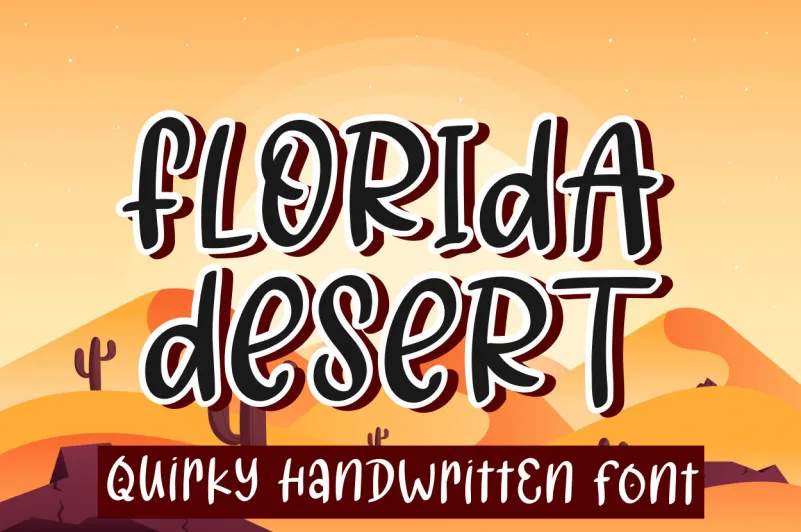
Esta é uma fonte display amigável e quirk, perfeita para quem quer dar um toque especial às suas criações visuais. O “Florida Desert Font” da designer sugiharto1790 será a escolha ideal para adicionar leveza à sua identidade visual, seja em cartões de boas-vindas elaborados ou posts sociais cativantes e emocionantes. Com um estilo divertido que promove momentos felizes, essa fonte é perfeita para personalizar materiais gráficos sem deixar de lado a beleza e a simplicidade que só uma boa fonte display pode proporcionar. Tente usá-la em sua próxima campanha digital ou projeto de design gráfico e sentirá o impacto instantâneo dessa opção única de fontes.